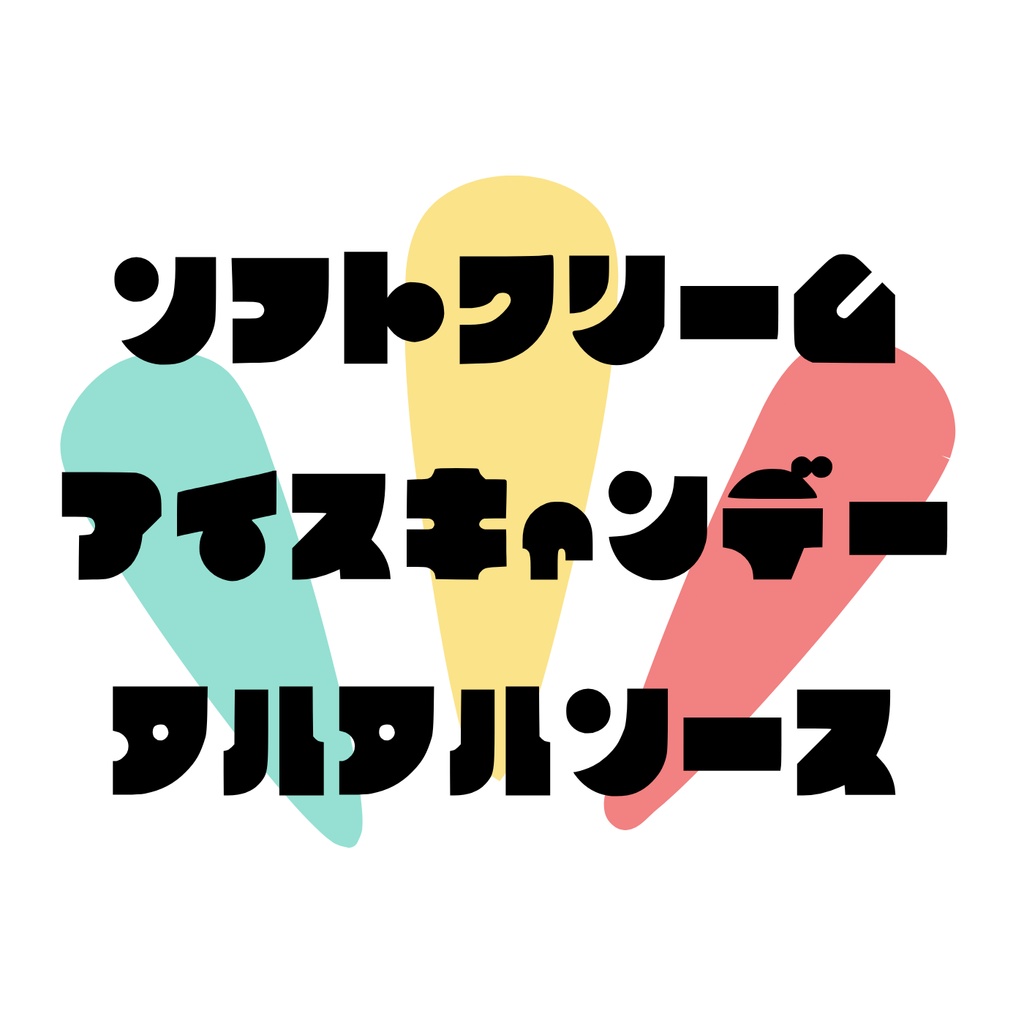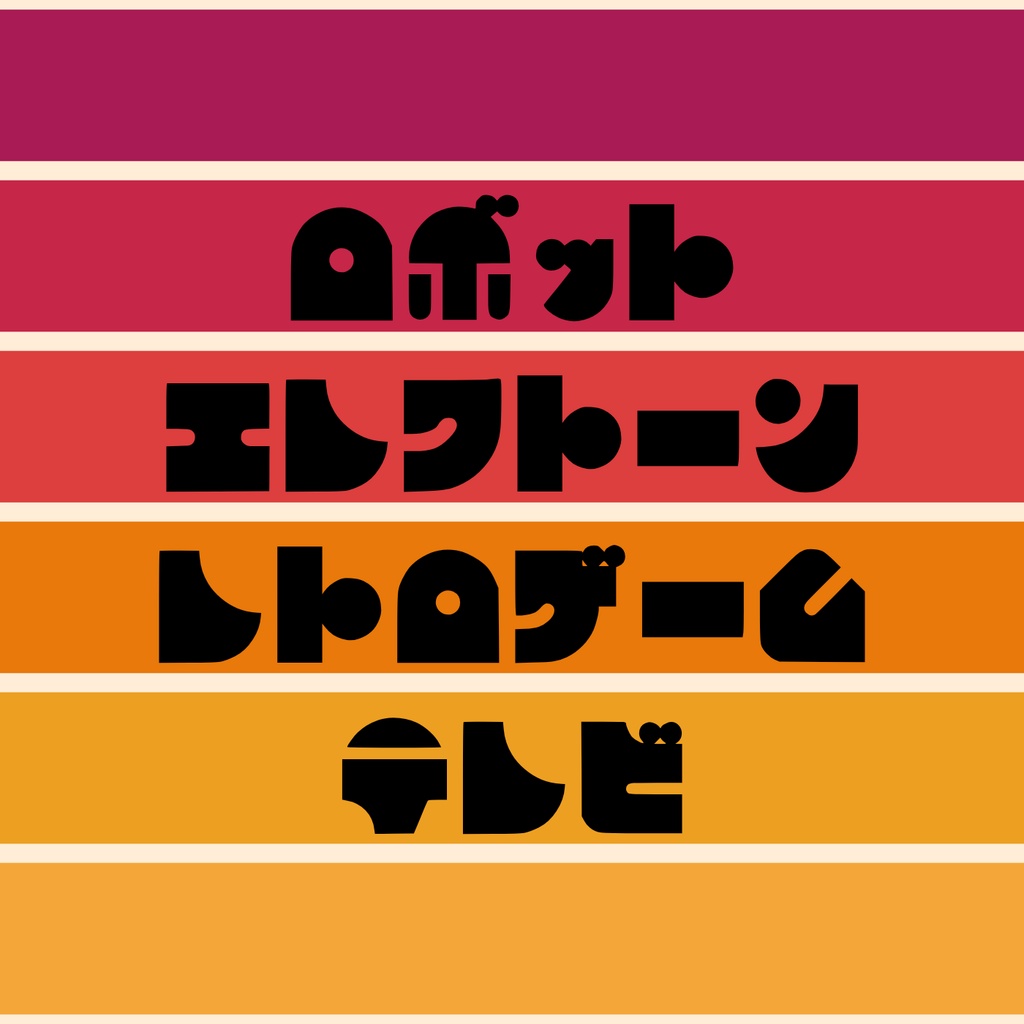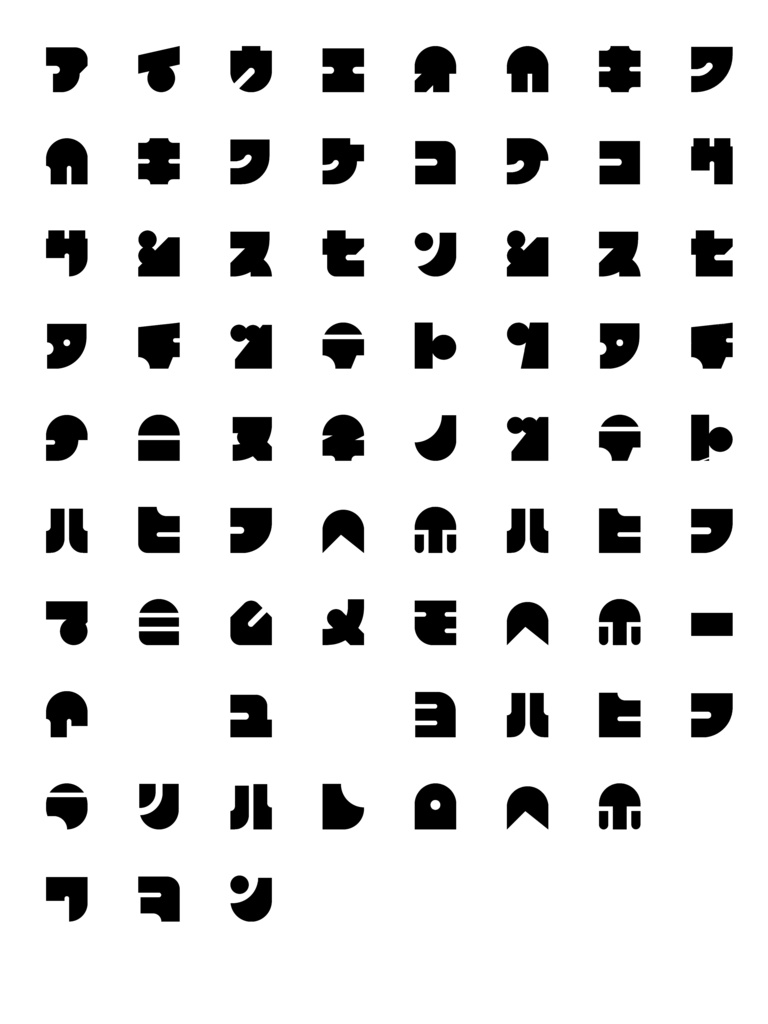
フォント【プテラノドン】
プテラノドンは、文字と形(シルエット)の要素を持ったフォントです。なるべくシンプルな形を目指しました。 フリーソフトで作成した都合上、75文字のみとなります。 ・収録文字:カタカナ(ァ、ィ、ゥ、ェ、ヴ、ヲなど除く)、・ー ・フォントデータ形式:otf この商品はフリーフォントです。著作権は製作者に帰属します。個人利用、商用利用可能です。画像化後の加工は可能です。拙い作品なので文字のバランスがあまり良くないことがあります。ァィゥェォが無いので、画像化後に小さくするなどでなんとかお願いします。ロゴに使いたい時輪郭を削るなど微調整可能です。フォントデータの改変・再配布・転載・転売は禁止です。公序良俗に反した用途での使用はお控えください。 当フォント使用時に生じたトラブル等に関して、一切の責任を負いません。